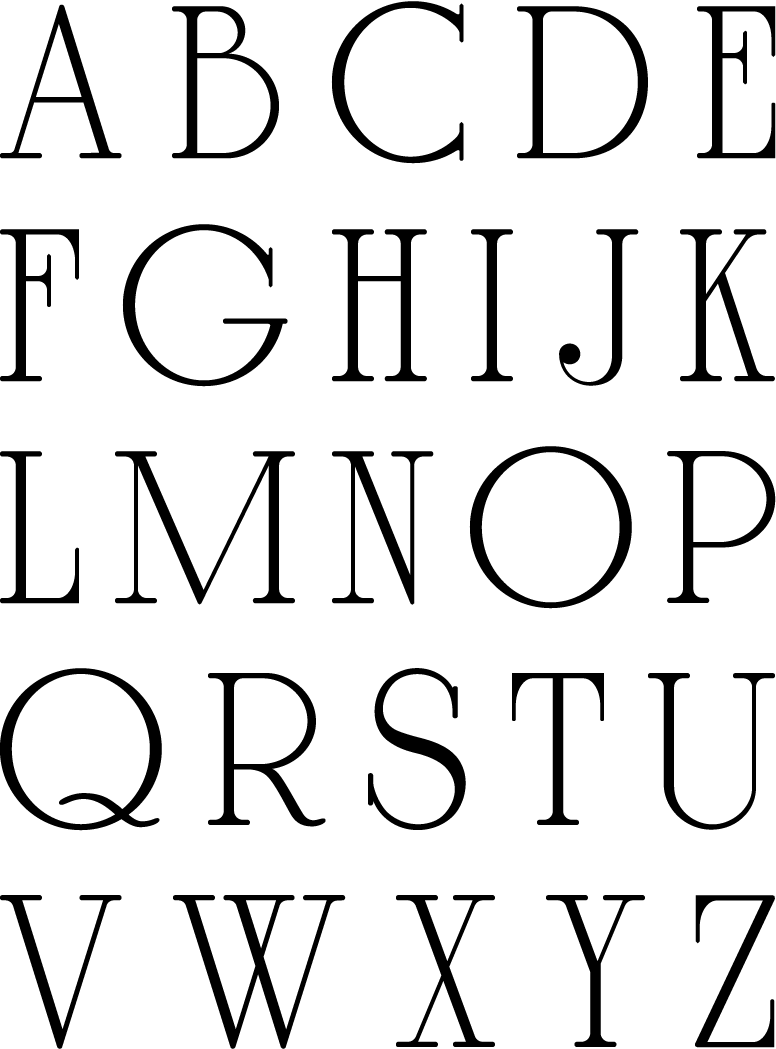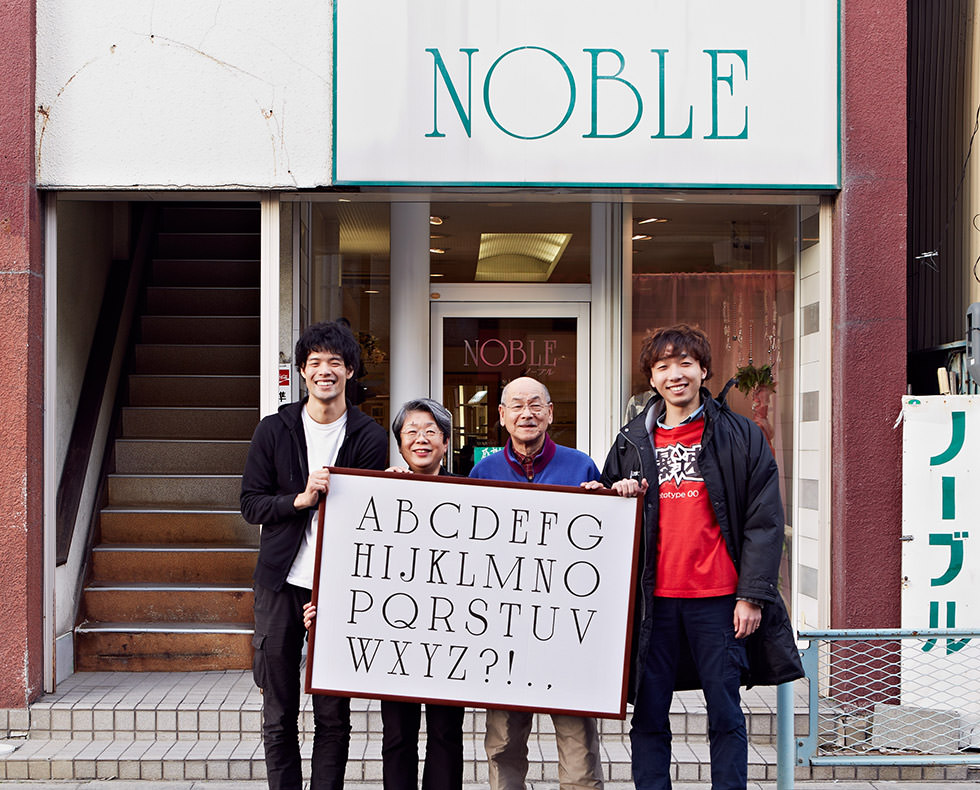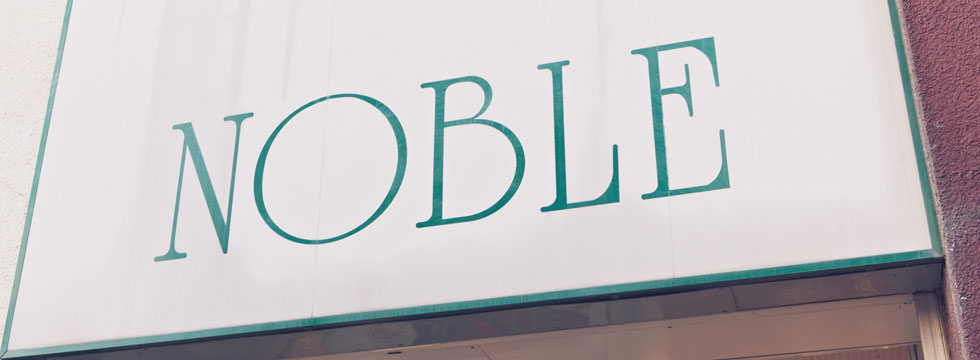
一見、普通のアルファベットだが、タテヨコの比率に良い感じのユルさが。E・F・K・L・Nあたりの可愛げのある佇まいに胸がキュンとなる。
「NOBLE」は1989年に開業したブティック。名前は「高貴」という意味だ。ワンブランドしか扱っていない。上品な感じ、高貴な感じ、それだけは欠かせないと夫婦は語る。書体はそのイメージに合わせて息子さんがデザインしたそうだ。「(震災後)商売のことは、あんまり気持ち無かったし、難しいだろうとおもってたけど、ところが、お客さんは衣類流されて無くなった人が多かったから、助かったーみたいな感じできてくれて。だから、前店やってたときより、新しいお客さんが増えたんです。お店辞められた方もいるじゃないですか。震災で。お店なくなっちゃったから、買い物する場所がないし、仮設に入ってる方で新しく来てくれるお客さんていうのも、増えましたね。そういう意味でも役に立ったのかなと思いますけどね。一度お買い上げ頂くと、これ何年も着てるんだよ、とか。気に入ってもらっている商品とか、影響でてるのかな。ですからそういう意味では、長いおつきあい。商品を通じてね。目標は、あと5年。5年は頑張ってやりたいし、お客さんのお手伝いしたいなって思ってますけどね。」